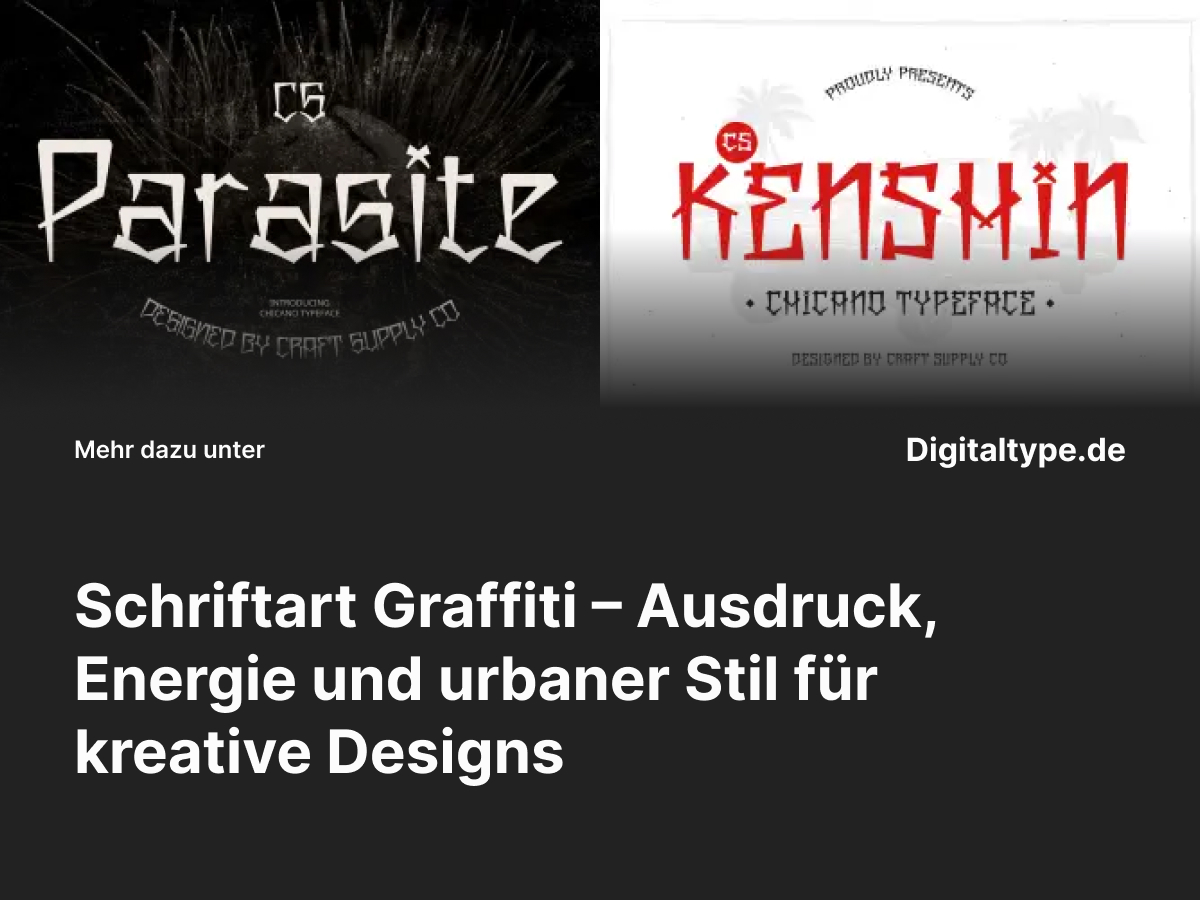
Eine Graffiti-Schriftart steht für Freiheit, Kreativität und Selbstbewusstsein. Inspiriert von der Street-Art-Kultur bringen diese Schriften eine dynamische, rebellische und zugleich künstlerische Stimmung in jedes Design. Ob für Poster, Musik-Cover, Mode-Labels oder Social Media – mit einer passenden Graffiti-Schrift verleihst du deinem Projekt einen markanten urbanen Charakter.
In diesem Artikel erfährst du, was eine Graffiti-Schrift ausmacht, wann du sie einsetzen solltest und welche Alternativen besonders gut zu deinem Stil passen.
Was ist eine Graffiti-Schriftart?
Der Begriff Schriftart Graffiti beschreibt Fonts, die auf der Ästhetik der Straßengraffiti basieren – oft mit kräftigen Linien, geschwungenen Formen und individuellen Sprayeffekten. Sie vermitteln Energie, Bewegung und einen Hauch von Rebellion.
Graffiti-Schriften haben meist eine expressive, handgemachte Optik, die sich stark von klassischen Fonts unterscheidet. Dadurch eignen sie sich perfekt für moderne, auffällige und kreative Designs.
Wann du Graffiti-Schriftarten verwenden solltest
- Branding für Streetwear- oder Musikprojekte: Ideal für Marken, die jung, kreativ und authentisch wirken wollen.
- Poster und Event-Grafiken: Perfekt für Festivals, Konzerte oder urbane Ausstellungen.
- Social Media Designs: Für Posts, die auffallen und Charakter zeigen sollen.
- Kunst- oder Illustrationsprojekte: Wenn du deinen Designs Energie und Emotion verleihen willst.
Eine Graffiti-Schriftart ist besonders dann effektiv, wenn du mit deinem Design Individualität, Stärke und eine kreative Attitüde ausdrücken möchtest.
Design-Tipps für Graffiti-Schriften
- Farbe ist alles: Nutze kontrastreiche Farben wie Neon, Schwarz oder Metallic-Töne, um den Street-Art-Look zu verstärken.
- Kombiniere Styles: Verwende Graffiti-Schriften mit klaren Sans-Serif-Fonts für Lesbarkeit und Balance.
- Experimentiere mit Texturen: Sprayeffekte, Schatten und Verläufe betonen den urbanen Charakter.
- Halte es authentisch: Zu glatte oder sterile Umsetzungen verlieren den echten Graffiti-Flair.
Die 6 besten Graffiti-Schriftarten für Designer
Hier sind sechs beeindruckende Graffiti-Schriftarten, die sich perfekt für kreative, urbane und energiegeladene Projekte eignen.
1. CS Parasite Chicano Graffiti Font
CS Parasite ist eine authentische Graffiti-Schriftart im Chicano-Stil. Mit kräftigen Linien, markanter Struktur und urbanem Flair bringt sie Street-Art direkt in dein Design. Ideal für Musikcover, Streetwear oder Tattoo-inspirierte Projekte.
2. CS Kenshin Chicano Graffiti Font
CS Kenshin vereint traditionelle Chicano-Graffiti-Ästhetik mit moderner Lesbarkeit. Ihre Balance aus Ornamentik und Struktur macht sie ideal für Logos, Poster oder kreative Markenauftritte mit Charakter.
3. CS Decima Graffiti Font
CS Decima ist laut, dynamisch und energiegeladen – genau wie echter Street-Style. Diese Schrift vermittelt Bewegung und Power, perfekt für Designs, die Aufmerksamkeit erregen sollen.
4. CS Rohan Drawn Font
CS Rohan bietet eine gezeichnete Struktur mit urbanem Look. Sie kombiniert handgemachte Linien mit moderner Klarheit und eignet sich hervorragend für kreative Projekte, Illustrationen oder Merchandise-Designs.
5. CS Corpse Drawn Font
CS Corpse hat einen dunkleren, raueren Charakter – perfekt für alternative Kunstprojekte oder düstere Street-Designs. Mit ihrer markanten Linienführung erzeugt sie eine rebellische und auffällige Atmosphäre.
6. CS Decima Drawn Font
Diese handgezeichnete Variante von CS Decima kombiniert Authentizität mit Urban Style. Ihre natürliche Textur und dynamische Formgebung machen sie ideal für kreative Typografie, T-Shirts oder Event-Branding.
Wie du die perfekte Graffiti-Schrift auswählst
Achte bei der Auswahl deiner Graffiti-Schriftart auf Lesbarkeit, Stil und Zweck deines Projekts. Während manche Fonts besonders expressiv sind, eignen sich andere besser für Branding oder Typografie im großen Stil.
Probiere verschiedene Kombinationen aus und achte darauf, dass der Text auch bei kleinerer Größe gut erkennbar bleibt.
Fazit: Graffiti-Schriftarten bringen Kreativität auf die Straße
Eine Graffiti-Schriftart ist mehr als nur eine Schrift – sie ist Ausdruck von Identität, Freiheit und künstlerischer Energie. Ob du sie für Branding, Streetwear oder digitale Kunst einsetzt – mit den richtigen Fonts kannst du deinen Projekten Tiefe, Dynamik und Persönlichkeit verleihen.
Die vorgestellten Alternativen bieten eine ideale Mischung aus urbanem Stil, Ausdrucksstärke und professionellem Design. Probiere sie aus und entdecke, wie sie deinem visuellen Auftritt den perfekten Street-Touch verleihen.